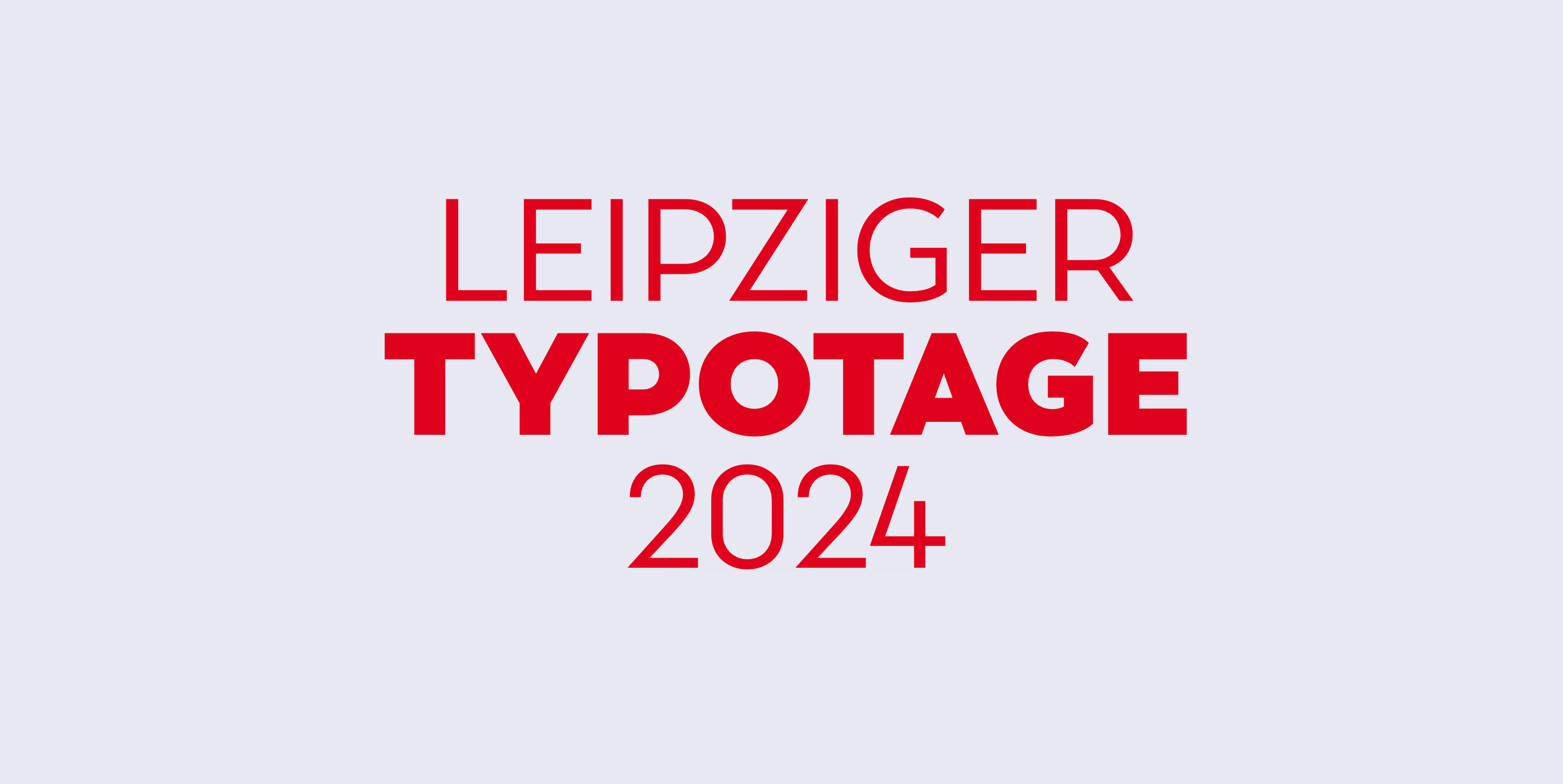
Ein kleiner * kann einen großen Unterschied machen. Selten zuvor stand ein typografisches Zeichen häufiger im Mittelpunkt von kulturkritischen Debatten. Derzeit nimmt das öffentliche Bewusstsein zu, dass Typografie gesellschaftliche Denkweisen und Handlungsmuster erzeugen, verstärken oder reproduzieren kann. Insofern kann sie gleichermaßen ausgrenzen und integrieren.
Aus diesem Grund werden sich die 29. Leipziger Typotage dieses Mal mit der Frage beschäftigen, wie geschlechtliche, soziale und ethnische Stereotypen in typografische Gestaltung visuell übersetzt werden. Doch ist eine stereotypenfreie Typografie überhaupt möglich? Und welche Rolle spielt Typografie für die Gestaltung von Inklusion und Diversität? Eingeladen sind Referent*innen mit vielfältigen kulturellen Hintergründen, die das Thema aus ihren sehr unterschiedlichen Perspektiven betrachten und diskutieren.